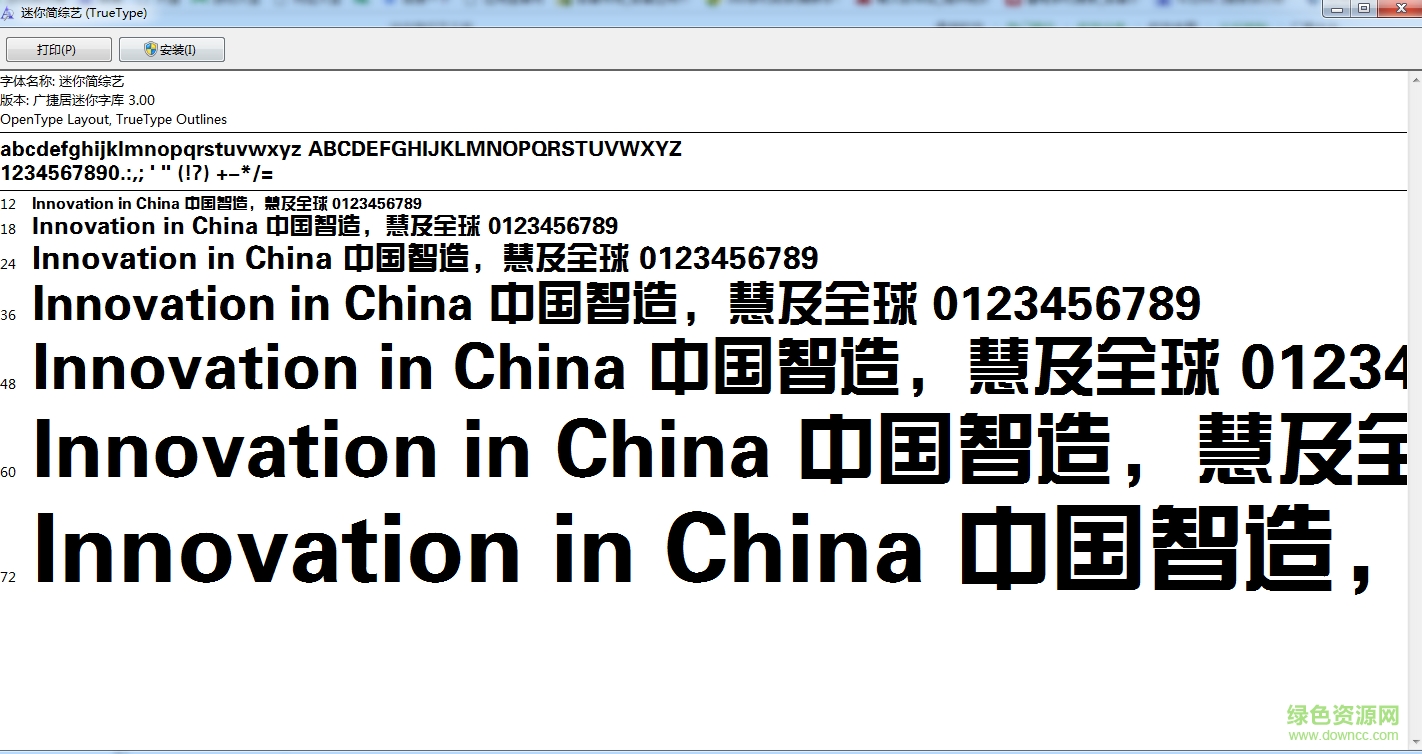
jzhongyi字体
jzhongyi是什么字体?jzhongyi字体是一款十分工整规范的迷你简综艺字体,该字体是黑体字体的一种变体,笔画粗壮,边角圆润,效果醒目,让你所创作的文章或者广告词句都会更加亮眼突出哦,需要的小伙伴快来绿色资源网下载吧!
jzhongyi字体特点
jzhongyi是一种常用的美术字体,字体偏扁平化,常被用于广告、报刊等的标题。
jzhongyi字体